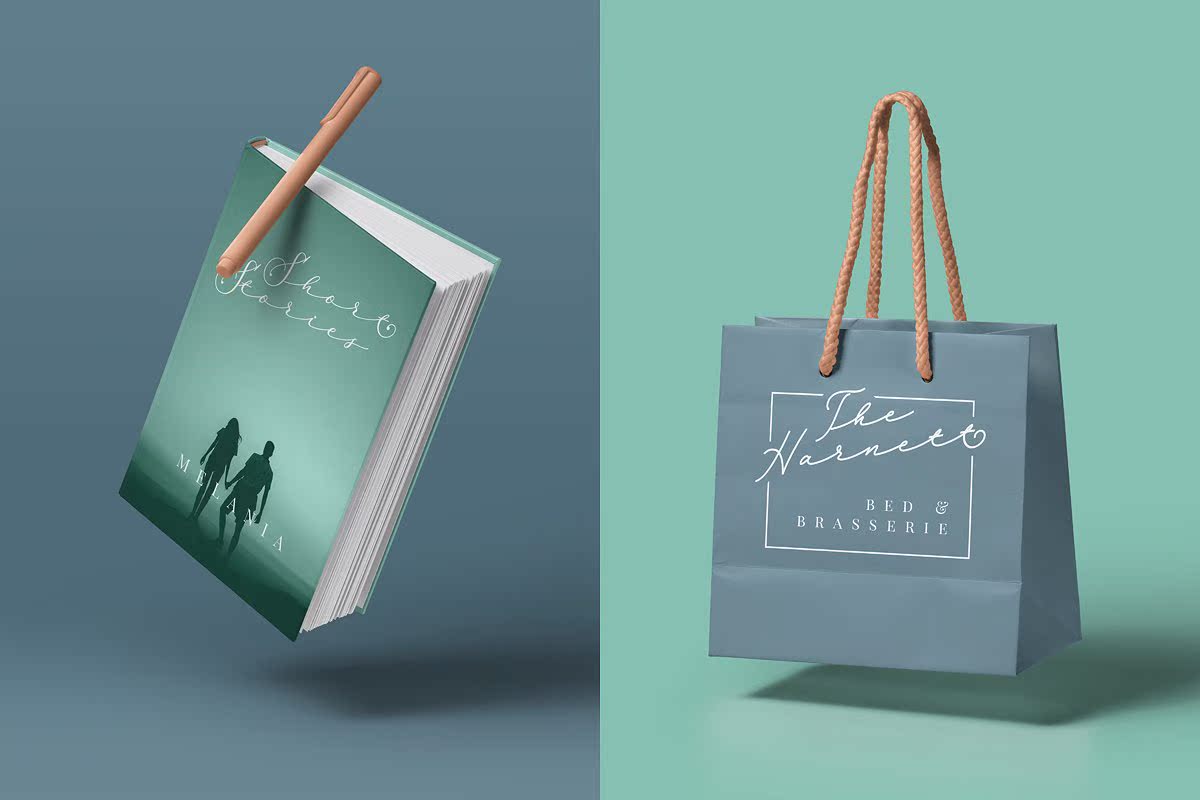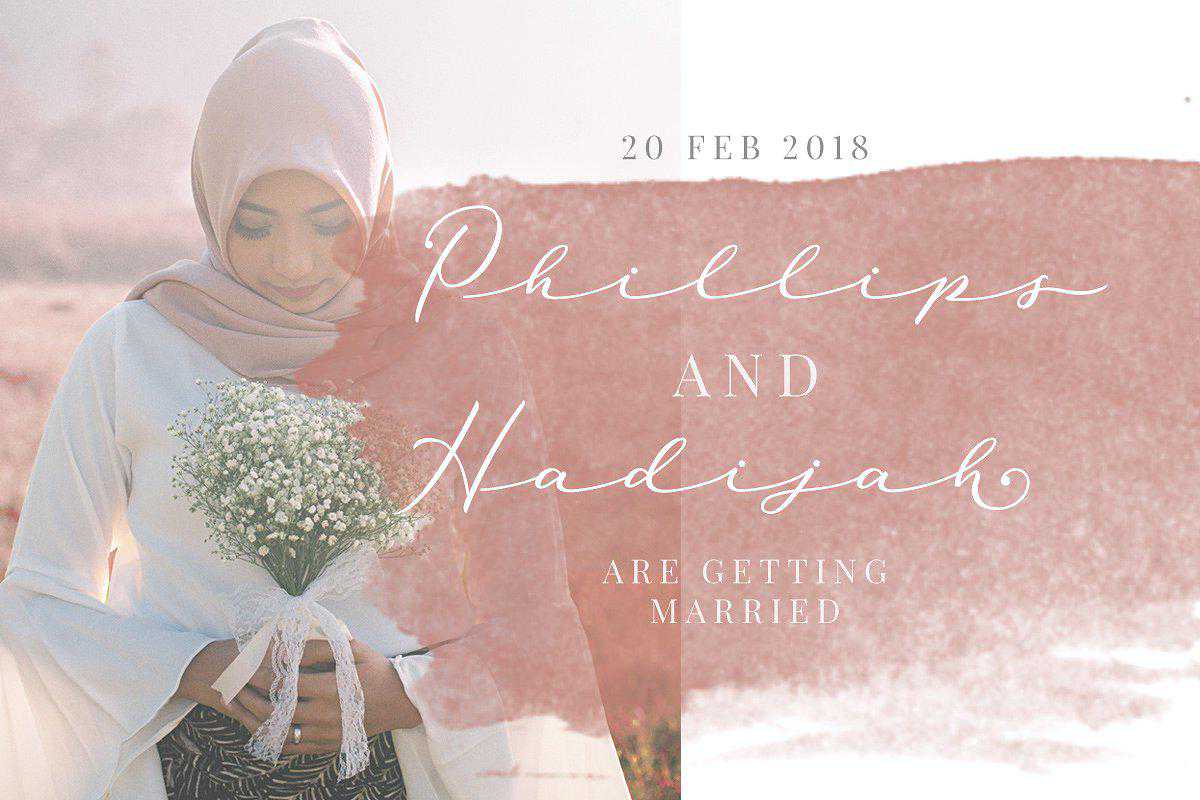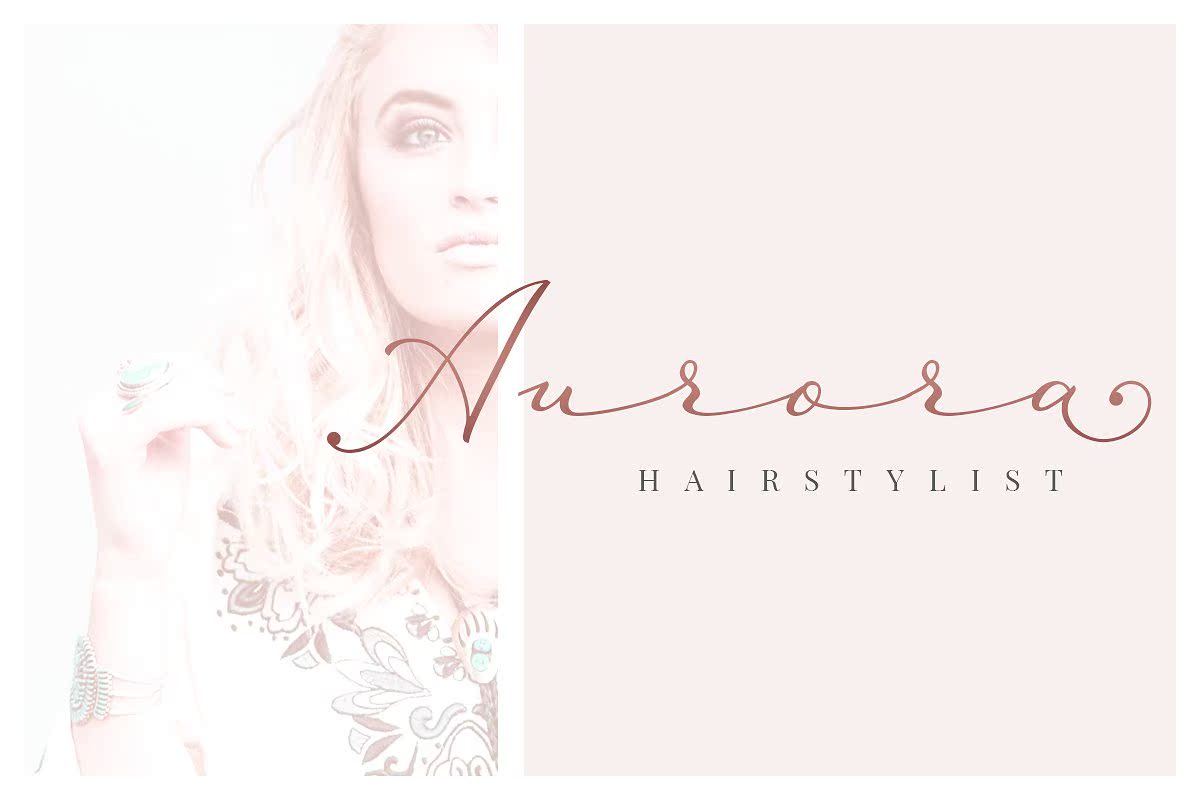
Hellotomelania说,这是因为它是由自然手写创造的,并给出了你所期望的女性形象。它们的规则消除带来了个人和独特的感觉,非常适合签名、婚礼、时尚、标题、引用等。它也包括大写字母、小写字母、标点符号、符号和数字、文体设置交替、连字、,ETCAL也支持多语言。比如Hellotomelania,这是因为它是由自然手写创造的,并给出了你所期望的女性形象。它们的规则带来了个人和独特的感觉,适合于签名、婚礼、时尚、标题、引用等。它包括大写、小写、标点符号、符号和数字,文体设置交替、连字等支持多语言。